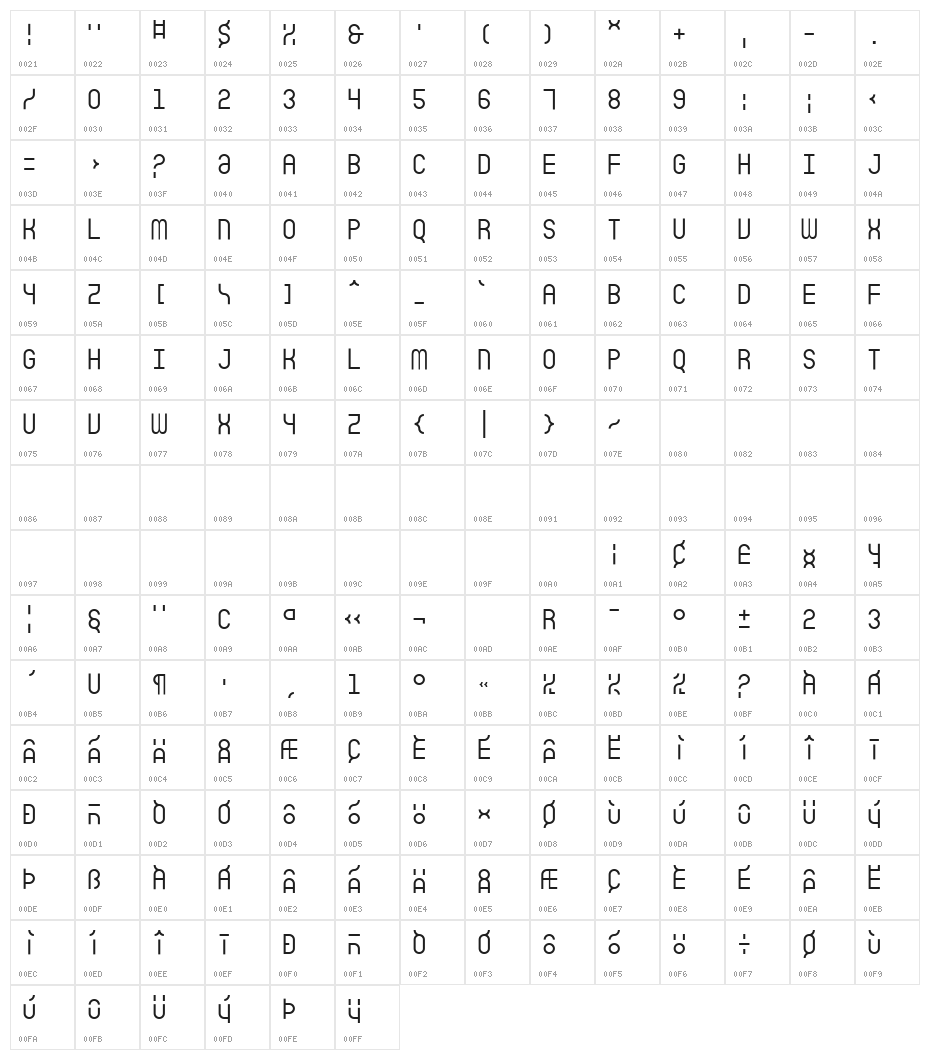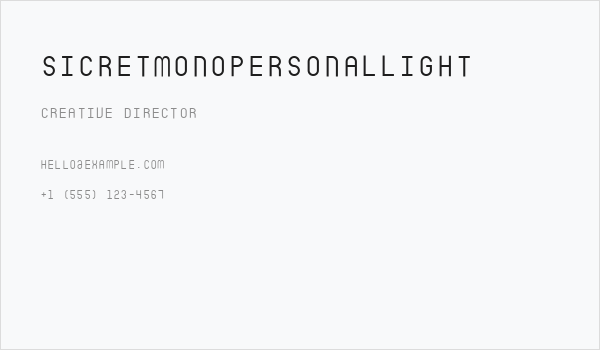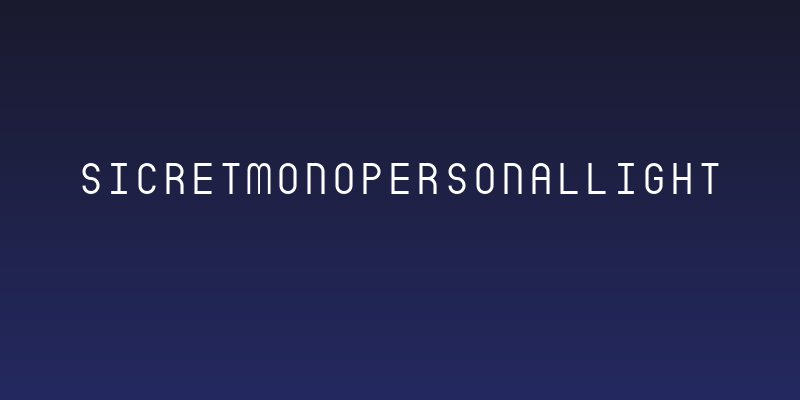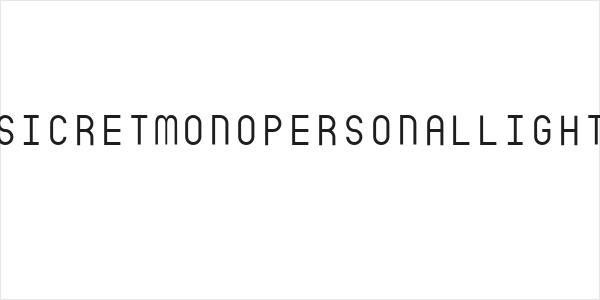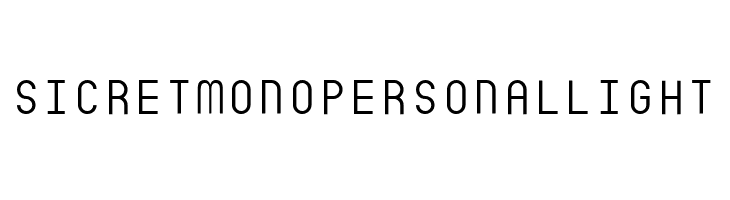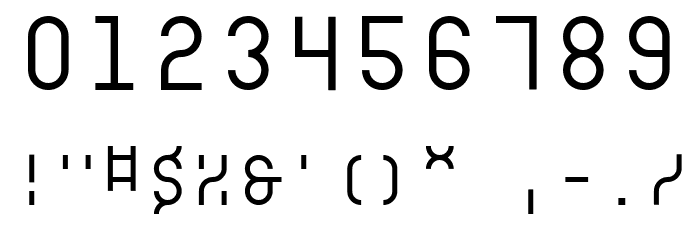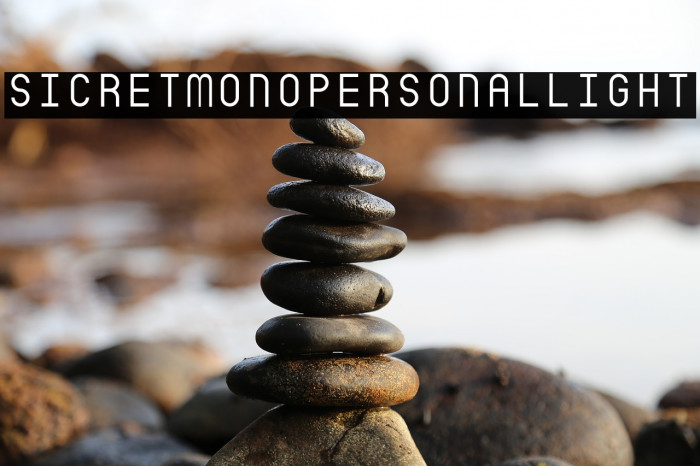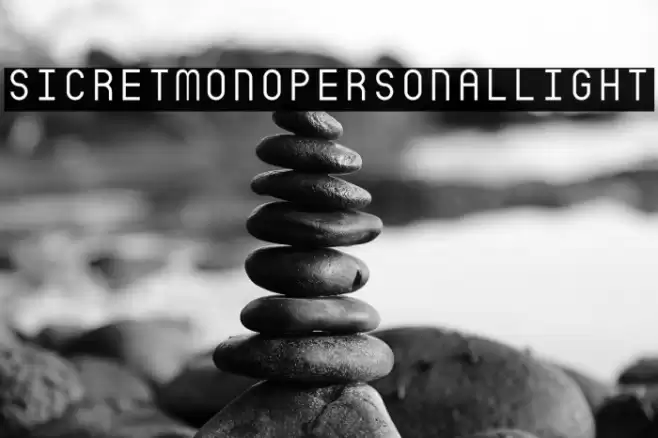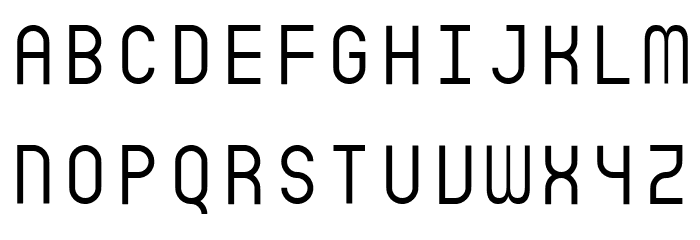
SicretMonoPERSONALLight Font
| حالة الاستخدام | Coding, Technical documentation, Data tables |
| مشاريع مقترحة | Ideal for coding environments, technical documentation, and data tables. It can also be used in minimalist design projects or branding that requires a clean and modern look. |